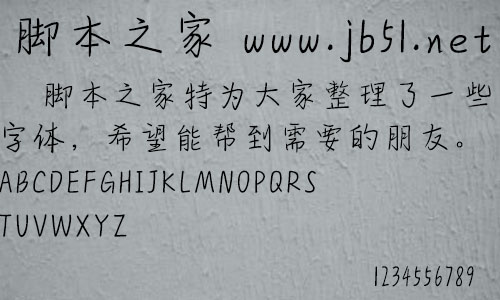
漢儀陌上云暮遲遲歸簡一款不錯(cuò)的藝術(shù)字體,由漢儀字庫出品,字體筆觸纖細(xì),字灑脫,具有很好的視覺感,適合應(yīng)用于藝術(shù)設(shè)計(jì)、平面宣傳設(shè)計(jì)、網(wǎng)頁設(shè)計(jì),書法字帖等領(lǐng)域,需要的朋友可以前來本站下載。